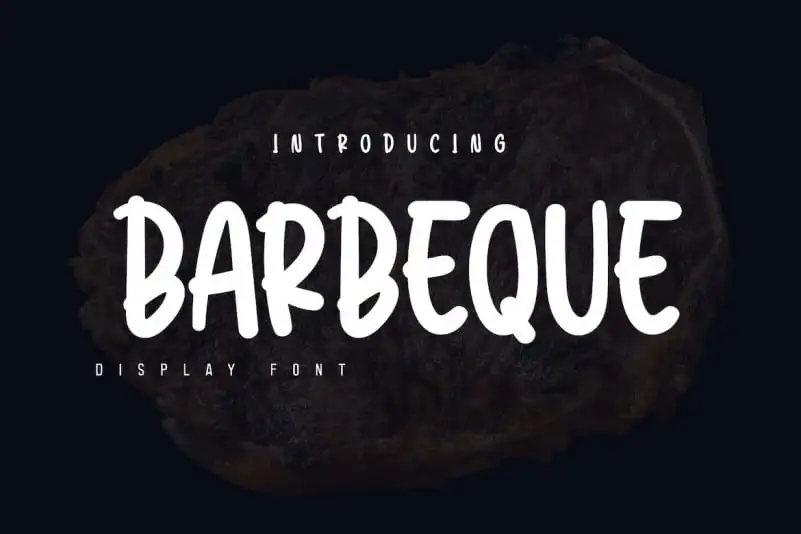
A Fonte ‘Barbeque Display Font’ é uma criação minimalista e divertida, projetada para conjurar a sensação do ambiente relaxante e estimulante de uma churrascaria. Seu estilo abstracto e escrita feita à mão inspira um mood descontraído, adequado tanto para aplicativos digitais quanto para materiais impressos, seja em banners, logotipos ou até mesmo em websites. Suas linhas leves e formas divertidas têm uma capacidade incrível de criar um impacto memorável que faz com que o público se divirta enquanto permanece atentos às mensagens transmitidas. Esta fonte é perfeitamente adequada para designers gráficos buscando adicionar um toque de diversão em seus projetos. Com seu estilo divertido e fácil de usar, a ‘Barbeque Display Font’ é uma opção ótima para promover ambientes festivos e churrascarias em sua próxima campanha visual.